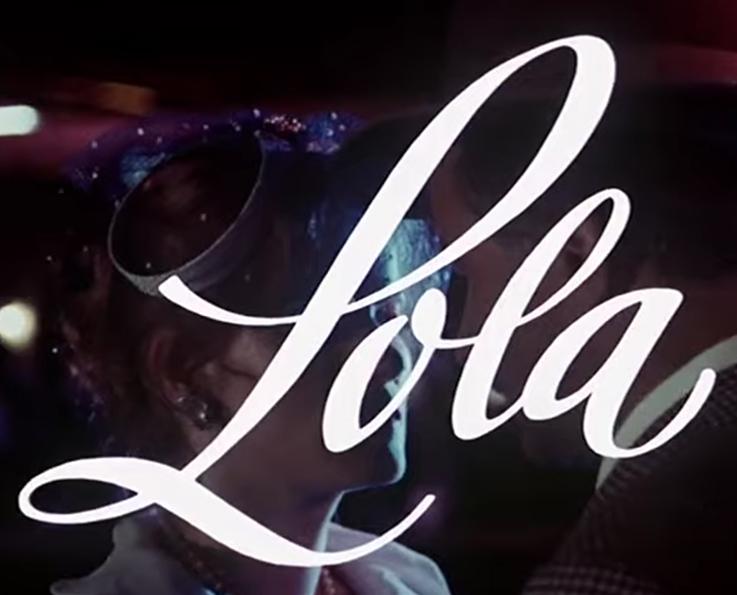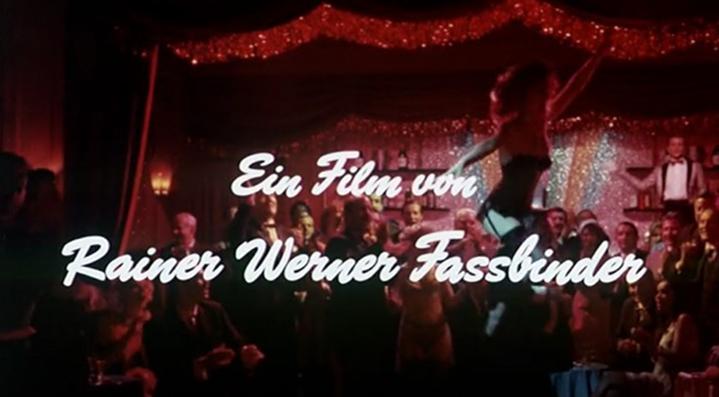
Titelschrift von Fassbinders »Lola«
Möglicherweise sind es ja auch zwei verschiedene Scriptfonts. Oder einer mit Alternates (a). Oder ein handgeschnitztes »Lola« …
Welche Brush das genau ist, die das gesuchte F hat, müsste noch recherchiert werden.
"Lola" ist jedenfalls nicht aus der Brush.